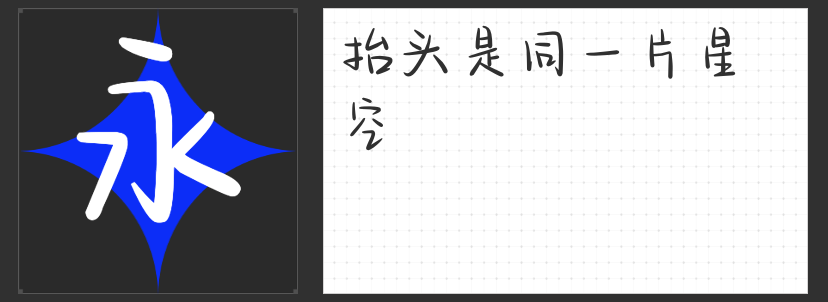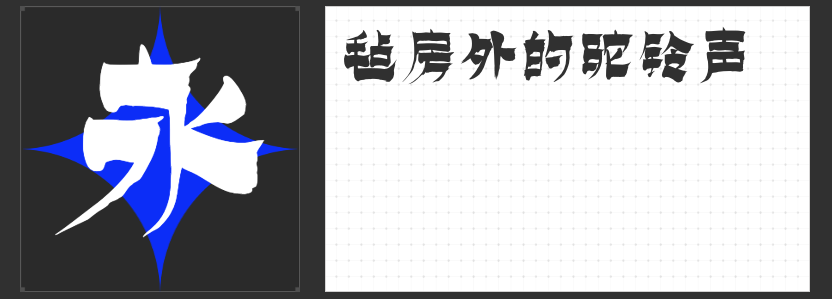
精选四款短视频字体推荐:让每一帧画面都充满个性与魅力
在短视频创作领域,字体不仅是信息传递的载体,更是塑造视觉风格、传递情感氛围的关键元素。以下四款专为短视频设计的字体,以其独特的风格与表现力,为创作者提供了丰富的选择。
1.小豆岛默陌乐童简:童真笔触,唤醒初心
这款字体以“童心是比野心更难得的梦想”为设计理念,采用上松下紧的儿童字结构,笔画简单稚拙,宽细一致,仿佛孩童用蜡笔在纸上留下的天真印记。它特别适合用于儿童教育、亲子互动类短视频,能瞬间拉近观众距离,营造出温馨、纯真的氛围。
2. 造字侠永刚漆书简繁:毛笔韵味,传统新生
作为一款创意毛笔手书字体,造字侠永刚漆书简繁笔画厚重,撇捺间尽显从容灵性,框架醒目且字型端庄。它完美融合了传统书法的韵味与现代设计的简洁,适用于包装印刷、广告设计等场景,在短视频中运用,能增添一份文化底蕴与艺术质感,特别适合历史、文化类主题。
3. 字圈也字综艺花字体:自信锋芒,个性张扬
这款字体横斜竖直,左低右高,折笔处钝角与直角交替,棱角时而圆润时而尖锐,展现出独特的视觉张力。其笔画坚定自信,仿佛诉说着“不在乎他人看法,遵从自我内心”的态度,非常适合用于时尚、潮流或个性展示类短视频,让画面充满自信与锋芒。
4. 小豆岛默陌枝桠简:水墨写意,潇洒自然
“愿你永远潇洒肆意!”是这款字体的寄语。它疏密有致,水墨书写风格明显,通过运笔节奏塑造线条粗细和节点,呈现出枯枝藤蔓般的造型感。在短视频中运用,能营造出一种传统与现代交织的美感,特别适合自然、艺术或文化类主题,让画面充满诗意与哲思。
这四款字体各具特色,无论是追求童真、传统、个性还是自然风格,都能为短视频创作增添独特的视觉魅力。选择合适的字体,让每一帧画面都成为传递情感、吸引观众的艺术作品。